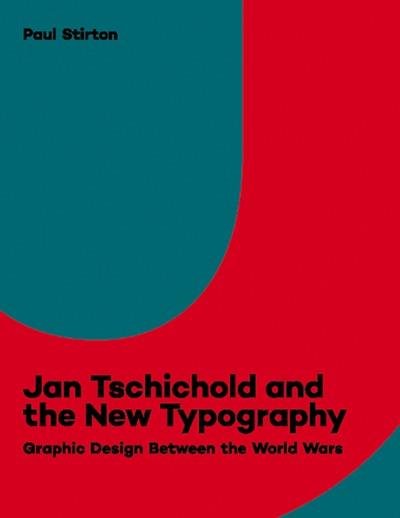
Livre neuf. Jan Tschichold and the New Typography. Graphic design between the World Wars. Catalogue de l'exposition présentée au Bard Graduate Center Gallery, New York, du 14 février au 7 juillet 2019. Nouvelle analyse de l'oeuvre du designer graphique, créateur de typographies et théoricien Jan Tschichold (1902-1974), à travers l'étude de ses collections d'illustrations, publicités, magazines et livres d'artistes tels que Kurt Schwitters, El Lissitzky, Aleksander Rodchenko et László Moholy-Nagy, et d'artistes-designers moins connus, comme Willi Baumeister, Max Burchartz, Walter Dexel, et Piet Zwart.
80 illustrations couleur et 20 en noir & blanc